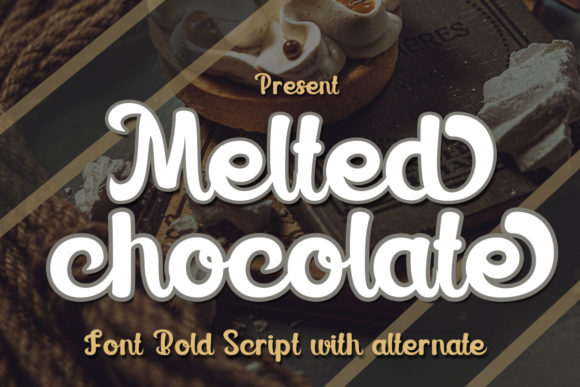
Плавленый шоколад - очень милый шрифт.
Причудливый и круглый литерный, этот шрифт скрасит каждый ваш дизайн. Этот шрифт закодирован PUA, что означает, что вы можете с легкостью получить доступ ко всем глифам и следам!